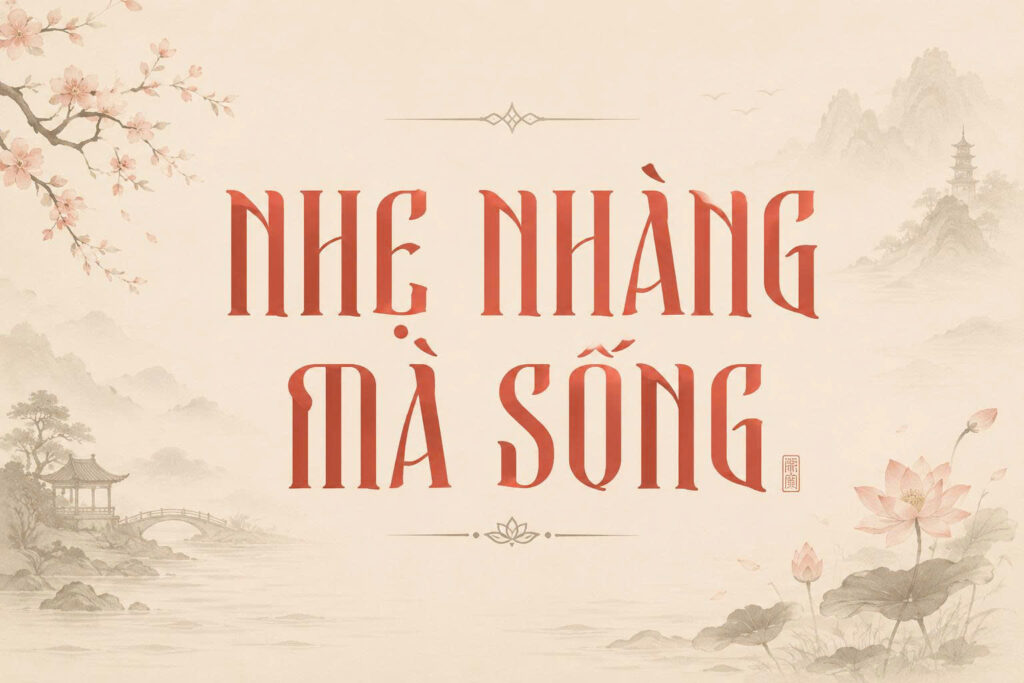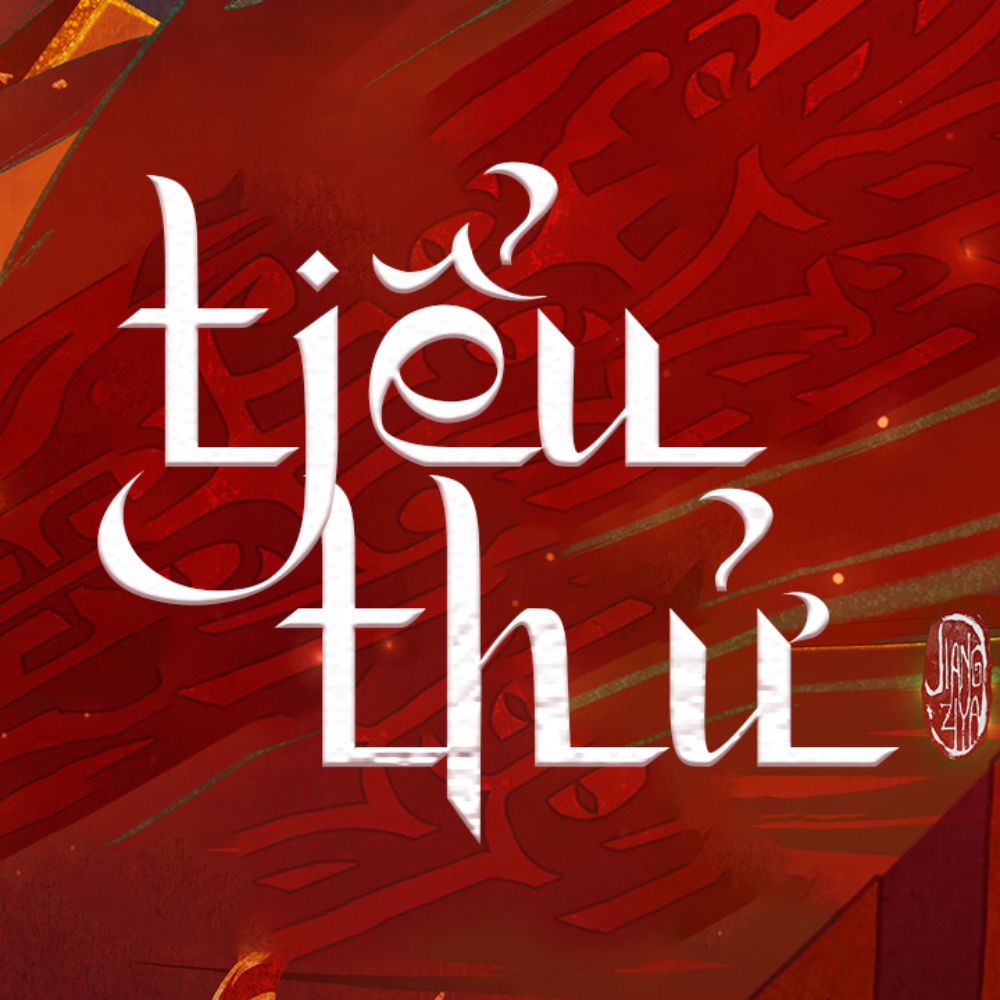
Trong các thiết kế mang âm hưởng hoài cổ hoặc phong cách Á Đông, việc lựa chọn kiểu chữ đóng vai trò quan trọng để tạo nên không gian nghệ thuật tinh tế. Font cổ trang Việt hóa với những đường nét mô phỏng bút lông, thư pháp giúp mang lại cảm giác thanh tao và xưa cũ cho tác phẩm.
Đặc điểm thẩm mỹ của dòng font cổ trang Việt hóa
Dòng font này thường sở hữu các nét vẽ có độ dày mỏng biến thiên linh hoạt, mô phỏng sinh động kỹ thuật viết chữ của các nghệ nhân thư pháp xưa. Điểm nổi bật của font chữ cổ trang Việt hóa chính là sự tinh chỉnh bộ dấu tiếng Việt sao cho cân đối với cấu trúc chữ gốc, giúp văn bản hiển thị mạch lạc và không gặp tình trạng lỗi ký tự. Điều này mang lại sự chuyên nghiệp cho các bản thiết kế đòi hỏi sự chỉn chu về mặt hình ảnh.
Bên cạnh yếu tố nghệ thuật, font việt hóa cổ trang còn sở hữu khả năng gợi mở cảm xúc mạnh mẽ về sự hoài niệm và tính truyền thống. Những nét cọ uốn lượn nhưng vẫn giữ được sự vững chãi giúp tạo nên điểm nhấn khác biệt so với các font chữ hiện đại thông thường. Đây là phương án phù hợp để truyền tải những thông điệp mang đậm bản sắc văn hóa và dấu ấn cá nhân trong từng dự án sáng tạo.
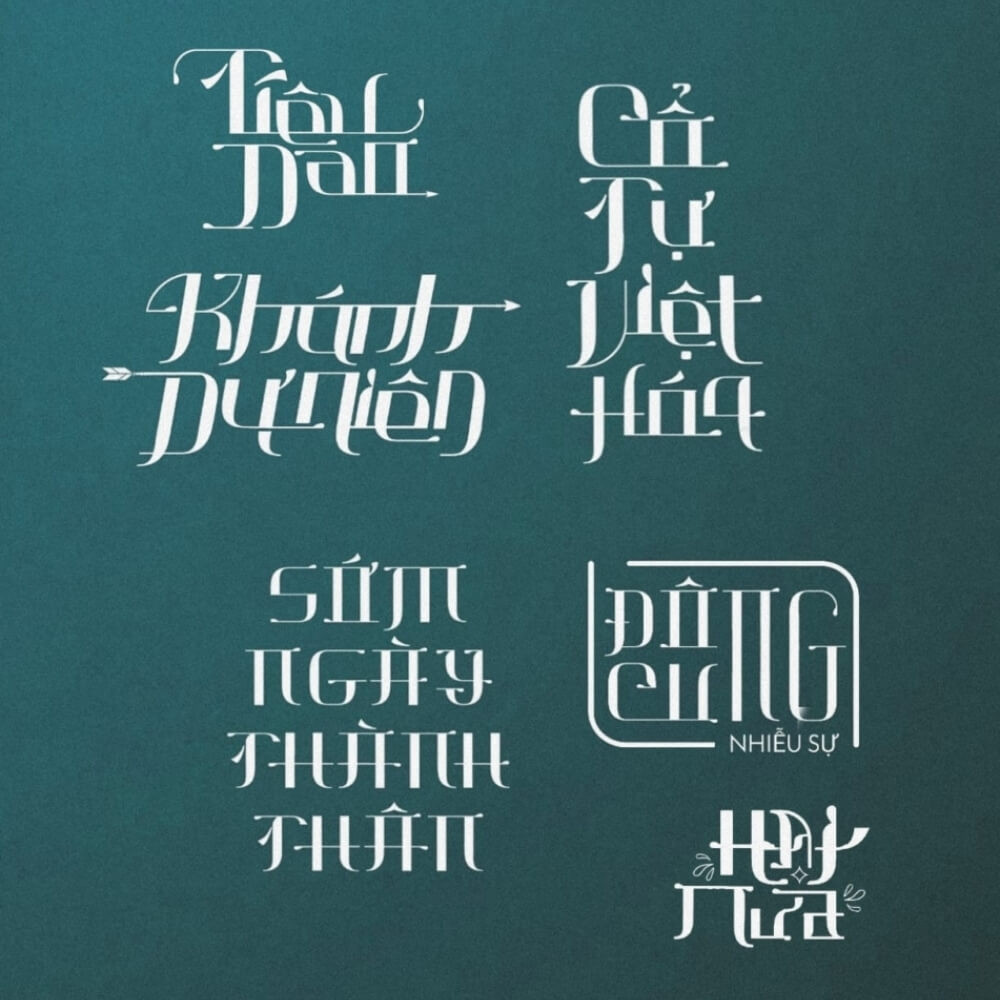
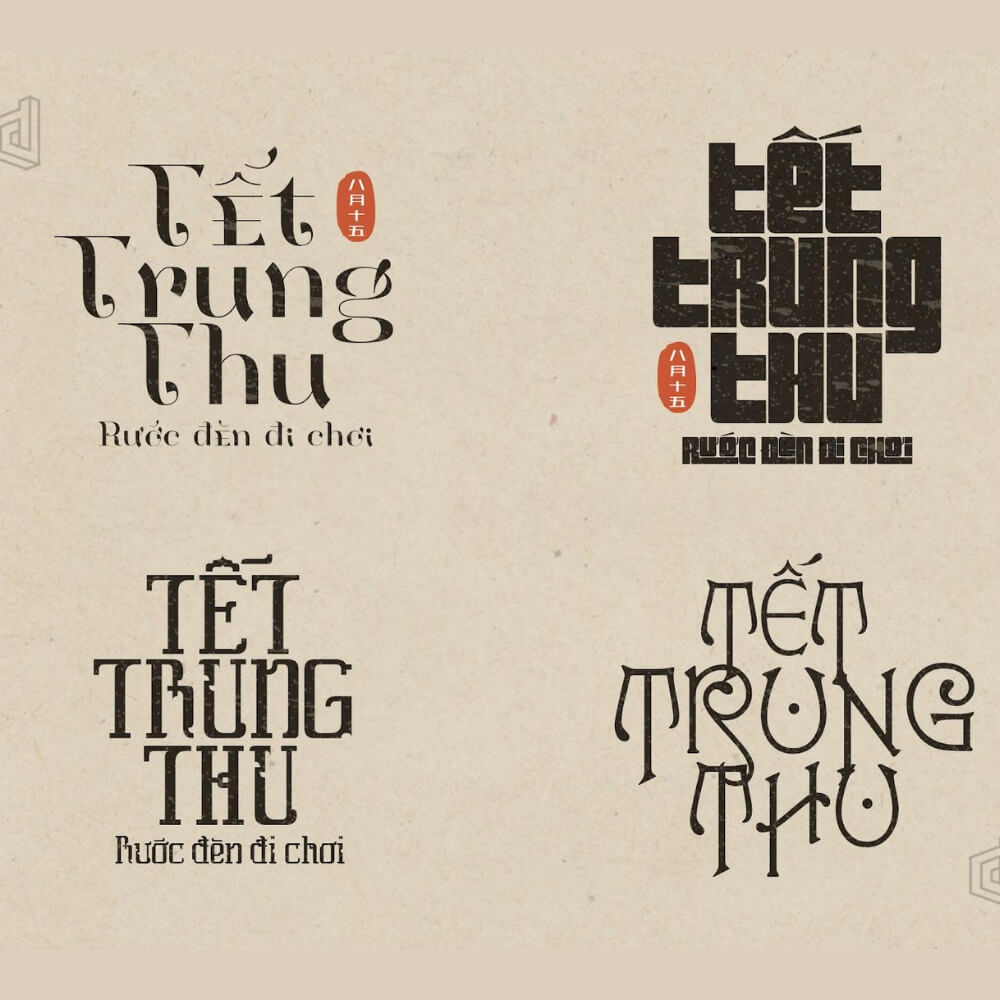
Gợi ý trình bày: Font phong cách cổ trang có nét chữ giàu tính trang trí và chiếm diện tích. Bạn nên ưu tiên sử dụng trên các nền màu trung tính hoặc vật liệu tự nhiên như gỗ, giấy mỹ thuật để làm nổi bật vẻ đẹp của từng vệt cọ vẽ.
03 Ứng dụng thực tế của font chữ cổ trang Việt hóa trong đời sống
Nhờ vẻ ngoài mang đậm tính nghệ thuật và sự trang trọng, bộ font này được ứng dụng linh hoạt trong nhiều hạng mục thiết kế và thi công hiện nay:
- Bảng hiệu cho Homestay và Nhà hàng: Những nét chữ cổ điển rất ăn ý khi xuất hiện trên các biển hiệu của các khu nghỉ dưỡng, homestay container mang phong cách mộc mạc hoặc Zen. Điều này giúp khách hàng cảm nhận được sự yên bình và gần gũi ngay khi bước chân vào không gian.
- Thiết kế Menu và Voucher: Sử dụng font chữ này cho các tiêu đề chính trên thực đơn quán trà, quán chay giúp khơi gợi cảm hứng về một lối sống thư thái và đậm chất truyền thống.
- Sử dụng trong font việt hóa edit truyện cổ trang: Đối với những bạn yêu thích lĩnh vực biên tập hình ảnh, bộ font này là công cụ đắc lực để trình bày các tựa đề truyện hoặc lời thoại nhân vật, giúp ấn phẩm mang đúng tinh thần của thời đại đang được mô phỏng.
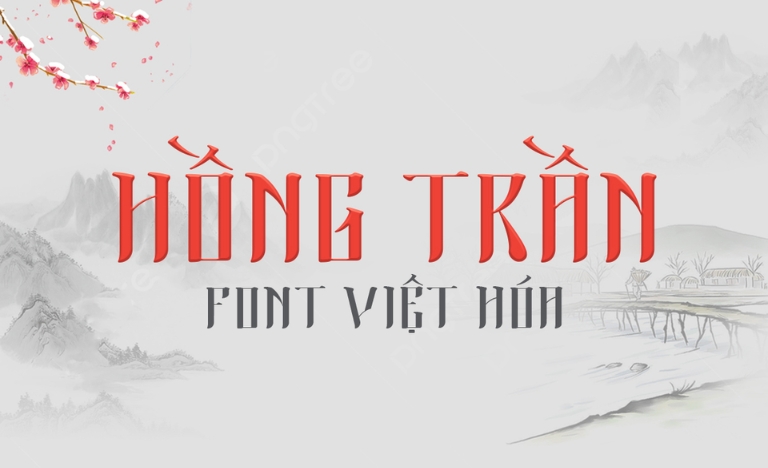
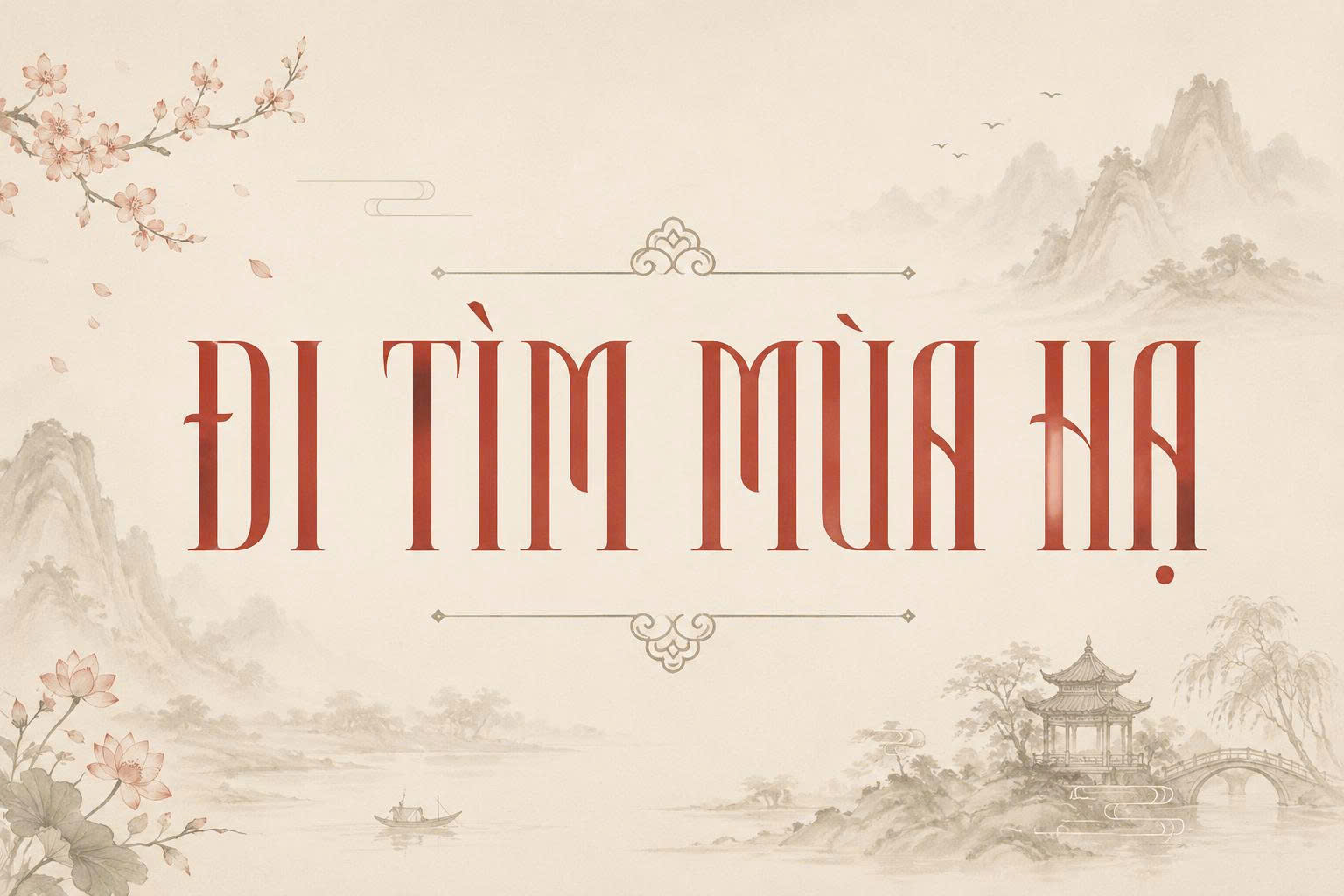
03 Lưu ý khi sử dụng font việt hóa edit truyện cổ trang và ấn phẩm đồ họa
Để khai thác hiệu quả vẻ đẹp của dòng font đặc thù này mà không làm rối mắt người xem, người thiết kế nên lưu tâm một số điểm sau:
- Hạn chế dùng cho văn bản dài: Do nét chữ có độ uốn lượn cao, bạn chỉ nên sử dụng font cổ trang cho tiêu đề, tên chương hoặc các câu trích dẫn ngắn. Sử dụng cho các đoạn nội dung dài sẽ gây khó đọc và làm mất đi sự tinh tế của tổng thể.
- Kiểm soát khoảng cách giữa các chữ: Một số ký tự cổ trang có nét móc vươn rộng, bạn cần nới rộng khoảng cách dòng (leading) để các chữ không bị chồng chéo lên nhau, giữ được sự thông thoáng cho bản thiết kế.
- Phối hợp cùng font tối giản: Để tạo ra sự cân bằng, hãy phối hợp font cổ trang (cho điểm nhấn) cùng các font không chân đơn giản cho phần nội dung chi tiết. Sự tương phản này giúp bản vẽ trở nên chuyên nghiệp và hiện đại hơn.